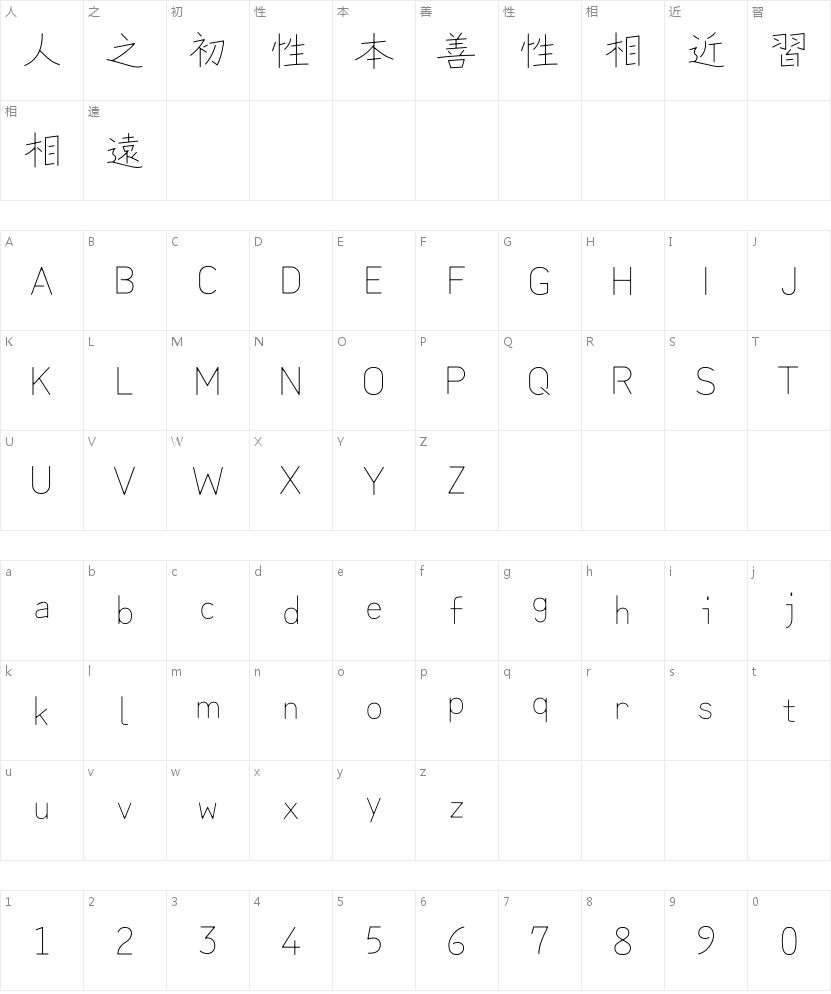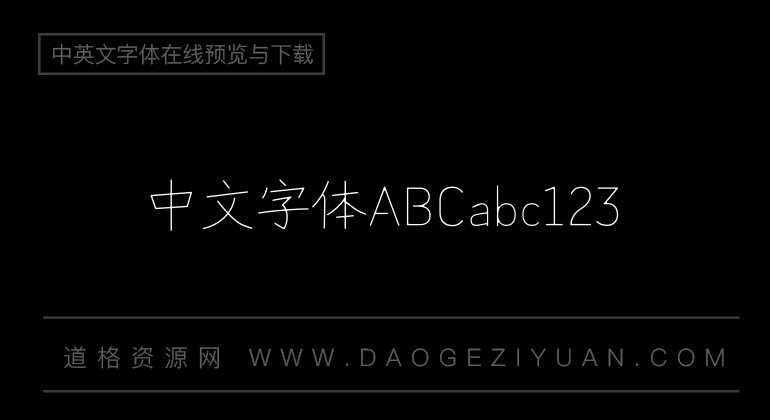
苦累蛙圆体-CJK-TC ExtraLight
苦累蛙圓體-CJK-TC ExtraLight 是一款中文字體,具有簡單清爽的風格,適合用於設計文宣、海報、廣告、書籍、網頁等各種文本排版場景。該字體擁有3000多個漢字,支援繁體中文,並有對應的英文字母、數字和標點符號,滿足中英文混排的需求。苦累蛙圓體-CJK-TC ExtraLight 字形工整、清晰易辨,低粗細度的設計讓文字顯得輕盈,使得長段落閱讀更加舒適。此外,字體擁有開放授權,可以免費商用,非常適合個人和中小企業使用。
苦累蛙圆体-CJK-TC ExtraLight是一款非常不错的手写艺术字体,具有很好的视觉感,适合于文化类的宣传设计、商业类品牌的广告和产品包装设计以及个性化文字排版等较多场景。
苦累蛙圆体-CJK-TC ExtraLight字符映射图